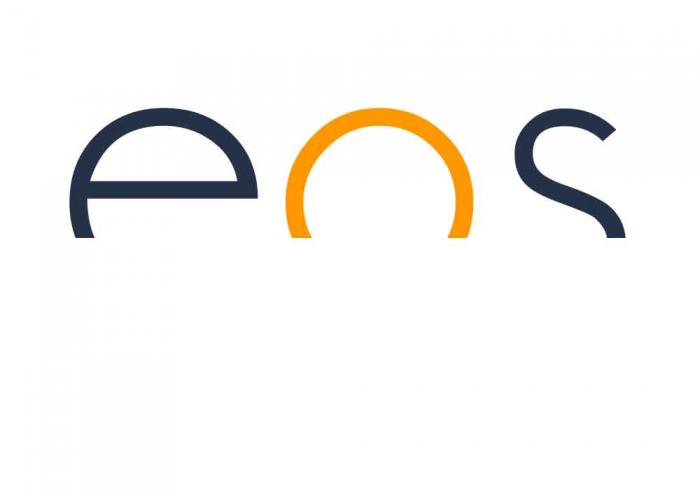
Konstruierte Schriften kombiniern
ich fange gerade an mich mit typografie zu beschäftigen und der Kombination von Schriftarten.
Nun bin ich gerade dabei Geosanslight in einem Logo zu verarbeiten und frage mich, welche Schriftart dazu passen würde.
Hab jetzt schon einige ausprobiert, aber irgendwie passt das alles nicht.
Habt ihr vielleicht Vorschläge?
wenn du ein beispiel zeigen würdest und ein paar infos dazu dann könnte man vielleicht was vorschlagen.
sonst ist es so wie – ich koche heute spaghetti, welche sauce soll ich dazu machen?
Naja, ich habe eos (kleingeschriben) in Geosanslight geschrieben (http://www.dafont.com/geo-sans-light.font) und das untere drittel weggenommen, da eos ja die göttin der morgenröte ist, dient das angeschnittene o als aufgehende sonne.post-26443-0-78017700-1396966749_thumb.j
Ich persönliche habe bis jetzt nur bei Geosans diese klaren und einfachen Linien (inklusive harten Kanten) gefunden, sonst hätte ich schon längst eine andere Schrift verwendet...
Unter eos möchte ich gerne noch was schreiben, einen slogan oder so.
Da habe ich bis jetzt auch geosans benutzt. Das geht schon.
Aber welche Schriftart könnte ich nun für den Haupttext benutzen?? Geosans liest sich in längeren Texten nicht so schön und Futura oder so kann ich mir noch nicht leisten...
Ist meine Frage jetzt verständlicher?
das eos hätte ich persönlich selbst gezeichnet (damit die beulen werschwinden ;) ) um das s optisch der breite anzupassen.
für ein slogan kommt einiges in frage, je nach dem in welche richtung die gesammt gestaltung gehen soll.
es gibt auch ernstzunehmende freie schriften wie z. b. die LATO
Das s anzupassen ist sicherlich eine gute Idee. Leider kann ich das selber noch nicht. Vielleicht bekomme ich sowas ja in der zukunft hin :)
Sowas lernt man, indem man es tut  :nicken: